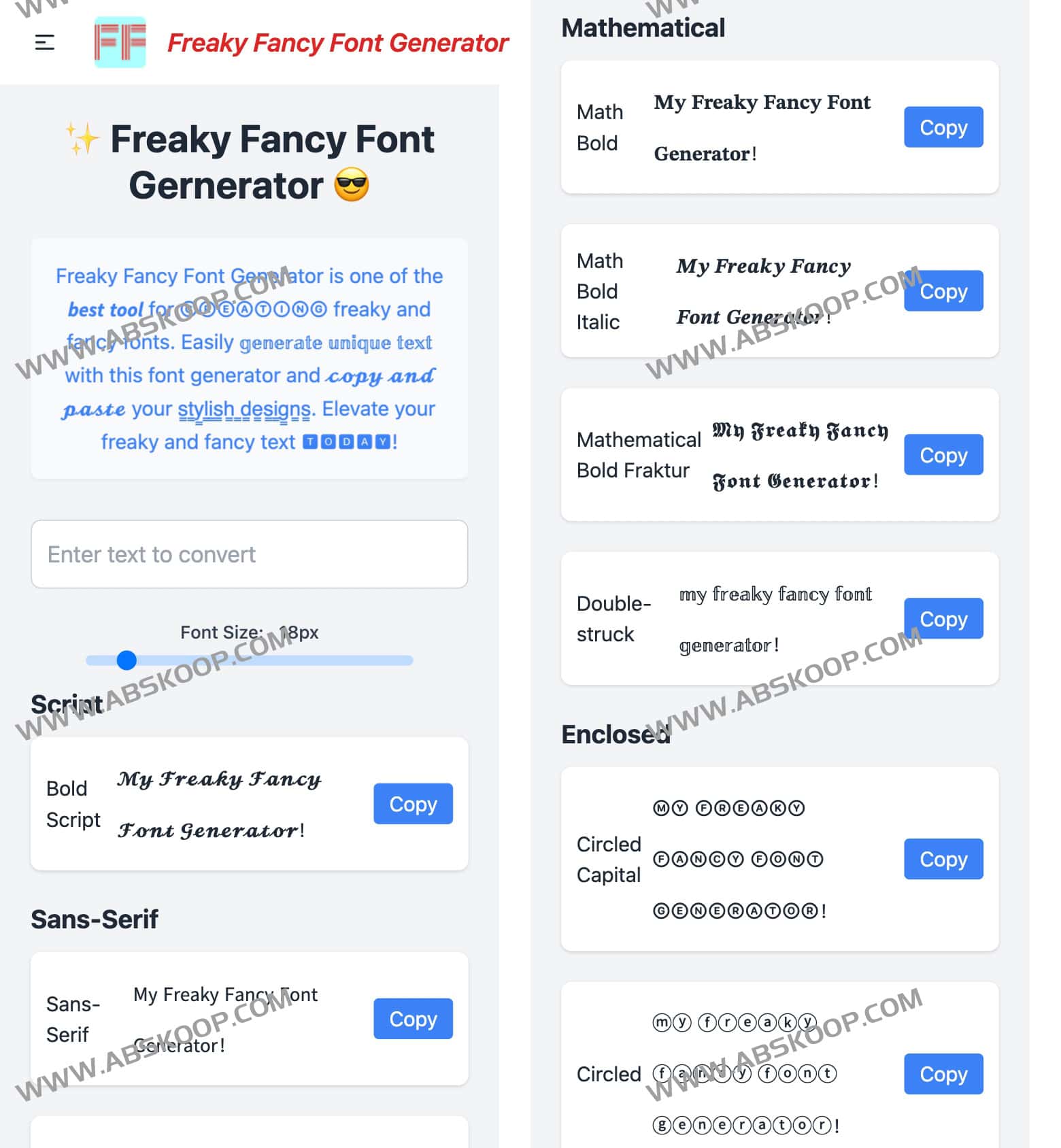
什么是 Freaky Fancy Font Generator
Freaky Fancy Font Generator 是一款便捷的在线文本转换工具,专门用于生成具有视觉冲击力的奇异字体。它内置了 40 多种独特的样式库,涵盖了 粗体、斜体、手写体 等多种风格,让普通文本瞬间变得与众不同。
该工具主打实时交互,用户在输入内容的同时即可看到转换效果,并支持灵活调整字体大小。生成的艺术文本可直接复制,非常适合用于社交媒体个人主页、网页设计点缀或各类创意个人项目,以提升内容的视觉吸引力。
1. 输入文本:在页面的输入框中键入你想要转换的文字。
2. 实时挑选:在下方生成的多种字体样式列表中,浏览并对比不同的视觉效果。
3. 自定义调整:根据需要调整字体大小,确保样式符合预期。
4. 复制分享:选中心仪的字体样式,将其复制并粘贴到社交平台或设计方案中。
• 社交媒体:美化 Instagram、Twitter (X) 或 TikTok 的个人简介和动态。
• 视觉设计:为网页元素或海报寻找快速的字体灵感。
• 个性化表达:在聊天或文档中创建独特的视觉标记。